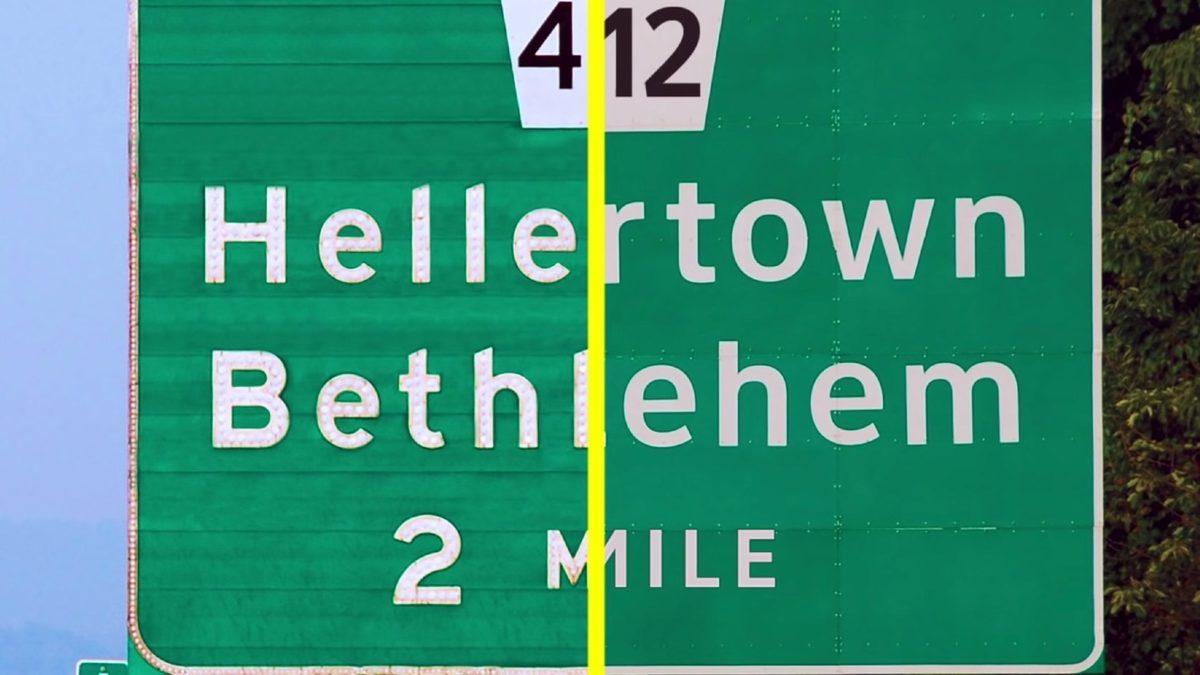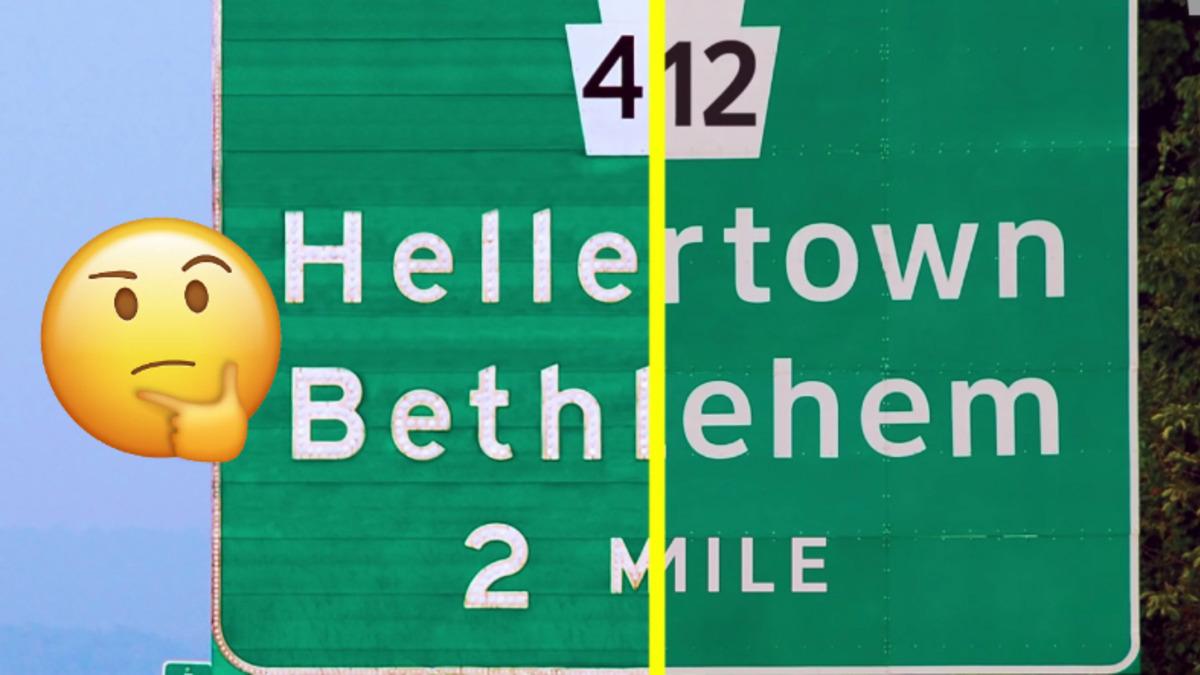
Türkiye’deki yol tabelalarını düşünün. Yazı tipi standarttır, sadece arka planlarındaki renkler ve işaretler değişebilir.
Ancak Amerika Birleşik Devletleri’ndeki yol tabelalarında, iki farklı yazı tipi kullanılıyor ve bunun, güvenlik amaçlı sebepleri var. Neler olduğuna bir bakalım.
Yol güvenliğini artırmak için iki farklı yazı tipi kullanılıyor.
ABD kara yollarında, farklı yol türleri ve hız limitlerine uyum sağlamak için iki farklı yazı tipi var. "Highway Gothic", 1948’den beri, daha yüksek hızlarda okunabilirliği artırmak amacıyla otoyollarda kullanıyor. Mesela bir çıkış veya dinlenme durağı arıyorsanız, büyük olasılıkla “Highway Gothic” yazı tipini göreceksiniz.
"Clearview" daha modern, okunaklı ve özellikle daha uzun mesafelerden rahatça okunabilmesi için tercih ediliyor. Daha ince harf çizgileri ve genişletilmiş harf aralıkları sayesinde gece görüşünü de iyileştiriyor.
“Clearview”, “Highway Gothic”te ortaya çıkan problemleri çözmek için kullanılmaya başlandı.
“Highway Gothic”in harfleri biraz daha kalın ve sıkışıktı. Ayrıca geceleri “halasyon” denilen durum ortaya çıkıyordu ve yukarıdaki gif'te gördüğünüz gibi harfler birbirine giriyordu.
1990’larda ortaya çıkan “Clearview”, harflerin boşlukları genişletilerek “Highway Gothic”ten kaynaklanan bu sorunları gidermek için bulundu ve 2004 senesinde ABD Karayolları tarafından onaylandı.
Özetle bu iki farklı yazı tipi, sürücülerin yol işaretlerini hızlı ve doğru bir şekilde anlayabilmesini sağlamak amacıyla tasarlanmış. Böylece, kara yolu güvenliği artırılarak, kazaların önlenmesi hedeflenmiş.